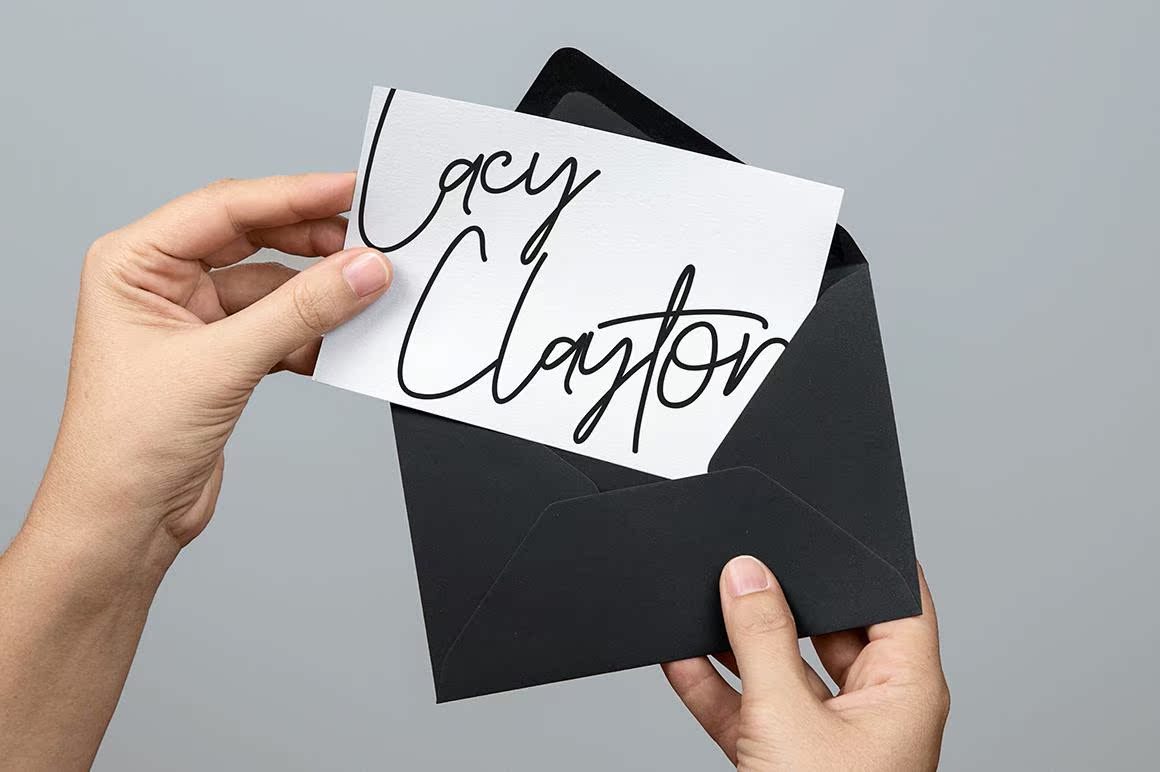
让您的设计具有经验证的手工手感。“ReillyBeckSignature”是不完全符合以下条件的其他产品:签名、文具、徽标、印刷报价、杂志封面、网站标题、服装、品牌、,包装设计和更多。赋予您的设计一种经过验证的手工制作的感觉。“ReillyBeckSignature”是一个不完全适合于签名、文具、徽标、印刷报价、杂志封面、网站标题、服装、品牌、包装设计和更多的包件。